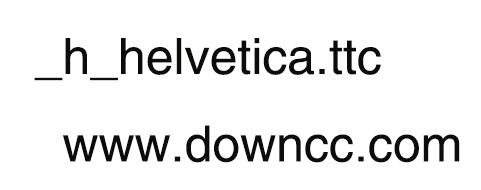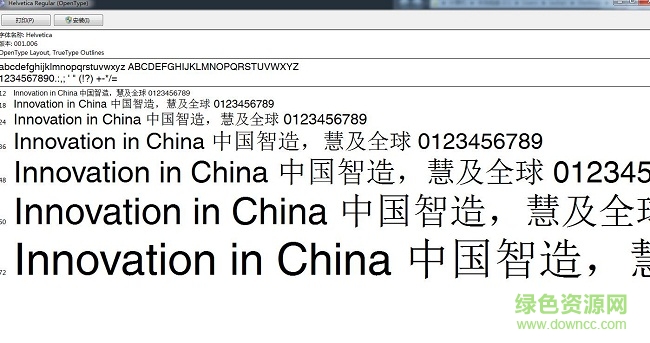
_h_helvetica.ttc字體是一款用在windows上的無襯線字體,結(jié)構(gòu)方正勻稱,線條筆直非常清晰,用在電子產(chǎn)品上閱讀效果良好,可以用作ps字體或廣告字體,歡迎下載!
現(xiàn)代字體設(shè)計(jì)趨于清晰簡(jiǎn)潔,為迎合現(xiàn)代特征,字體設(shè)計(jì)被簡(jiǎn)化,襯線逐漸被去除,線條也不再有粗細(xì)之分,干凈利落,更具機(jī)械繪制的特點(diǎn)。